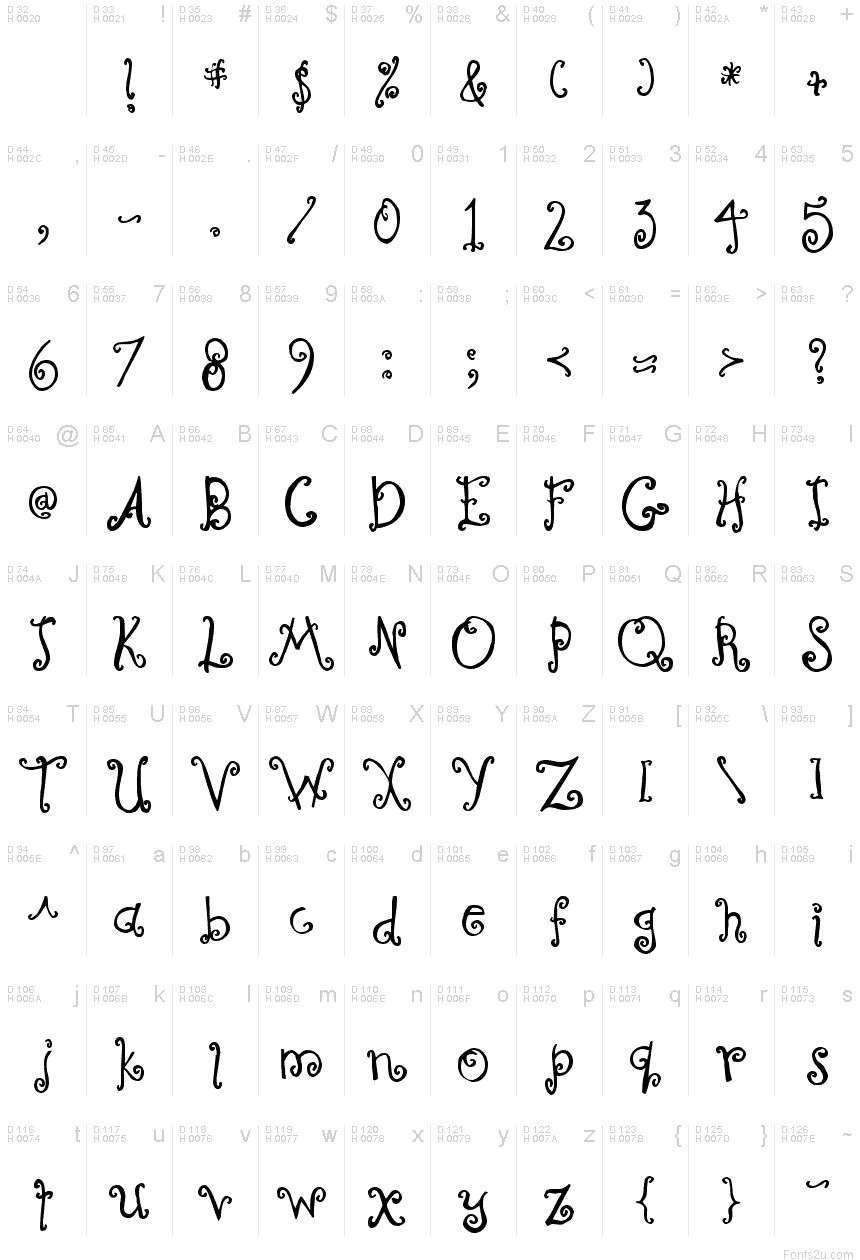
خط Curly Coryphaeus من تصميم Isabelle Trolio هو خط مجاني للعناوين يتميز بلفافات وتدرجات حبرية انسيابية مع دوامات كبيرة تمنحه طابعاً مرحاً يشبه حكايات القصص. الحروف تبدو خفيفة وليست ثقيلة، لذا حتى مع كل هذه الزخارف، تظل الكلمات مفعمة بالحيوية وسهلة القراءة من نظرة واحدة.
يعمل خط Curly Coryphaeus بشكل رائع على أغلفة كتب الأطفال، ودعوات الحفلات، وشعارات متاجر الحرف اليدوية، والتغليف المصنوع يدوياً، وسبورات المقاهي، وملصقات الفصول الدراسية، والمنشورات الترفيهية على وسائل التواصل الاجتماعي. يبرز هذا الخط المجاني بشكل أفضل عند استخدامه بأحجام كبيرة، ويتناغم بشكل جميل مع خط "سان سيرف" بسيط عندما تريد أن تكون اللفافات هي التي تتحدث.